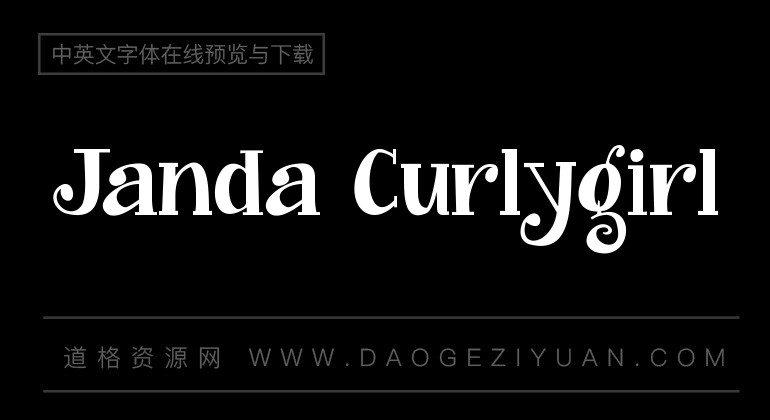
Janda Curlygirl是一种手写风格的字体,由美国字体设计师Kimberly Geswein创造。这种字体具有自然、轻松和女性化的感觉,因此非常适合用于女性品牌、手工艺品、婚礼邀请和文具等领域的设计。 Janda Curlygirl字体的特点是它的笔画充满了弯曲的线条和卷曲的装饰,这使得它看起来非常有趣和有个性。此外,它还包括了大量的手写风格的字母、数字和符号,这使得它非常适合用于设计中的标题、标志和其他大型文本。 总体来说,Janda Curlygirl字体是一种充满活力和个性的字体,非常适合那些希望在设计中添加一些女性化和手写风格的人。内容介绍
Janda Curlygirl是一款非常不错的手写艺术字体,具有很好的视觉感,适合于文化类的宣传设计、商业类品牌的广告和产品包装设计以及个性化文字排版等较多场景。